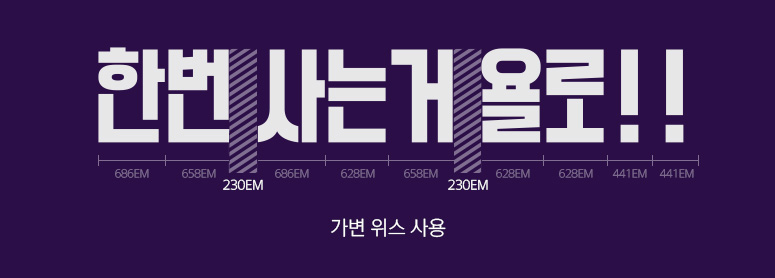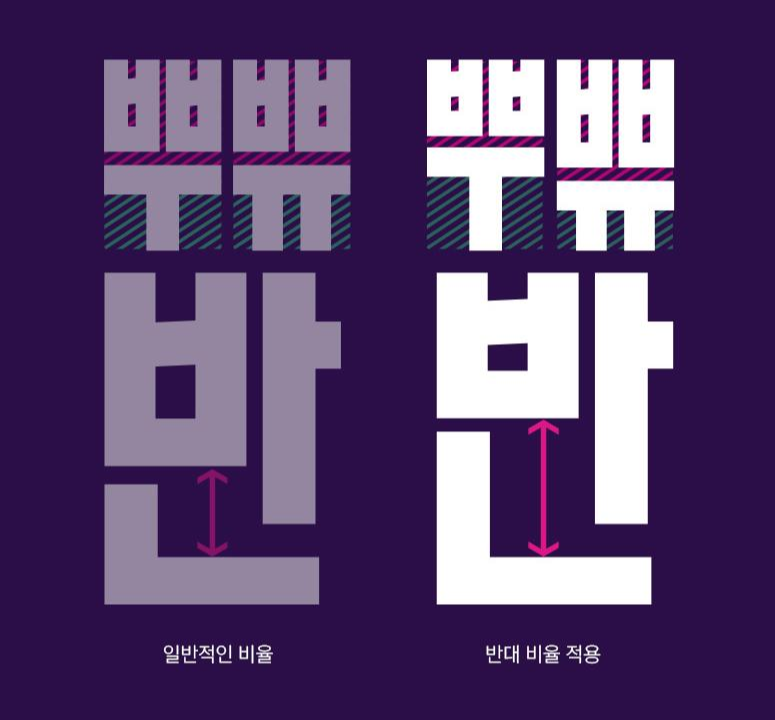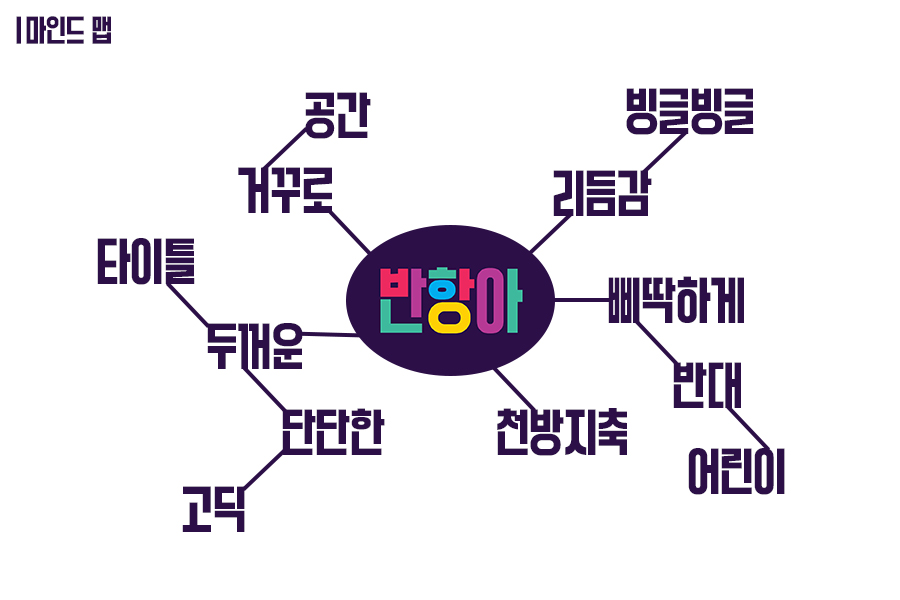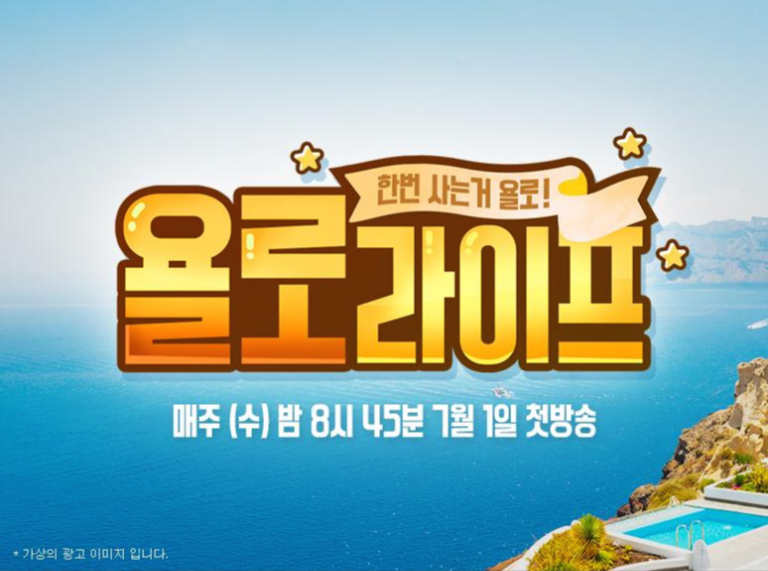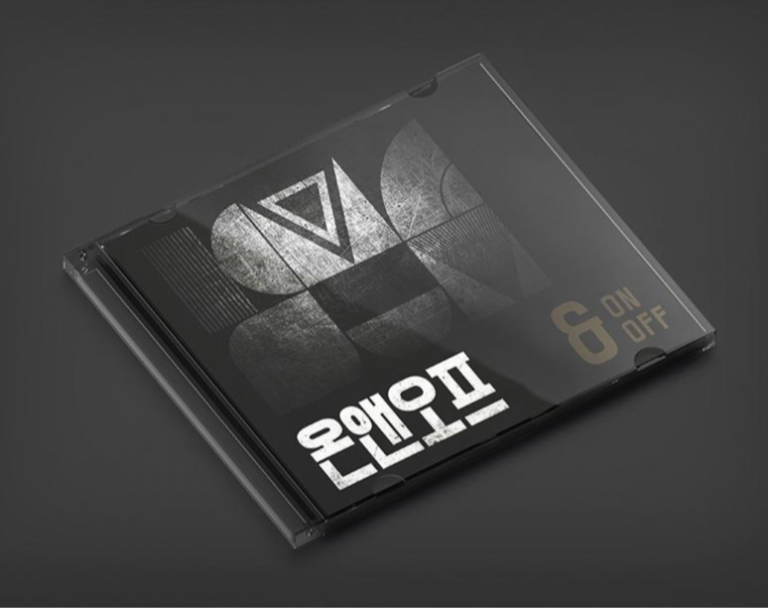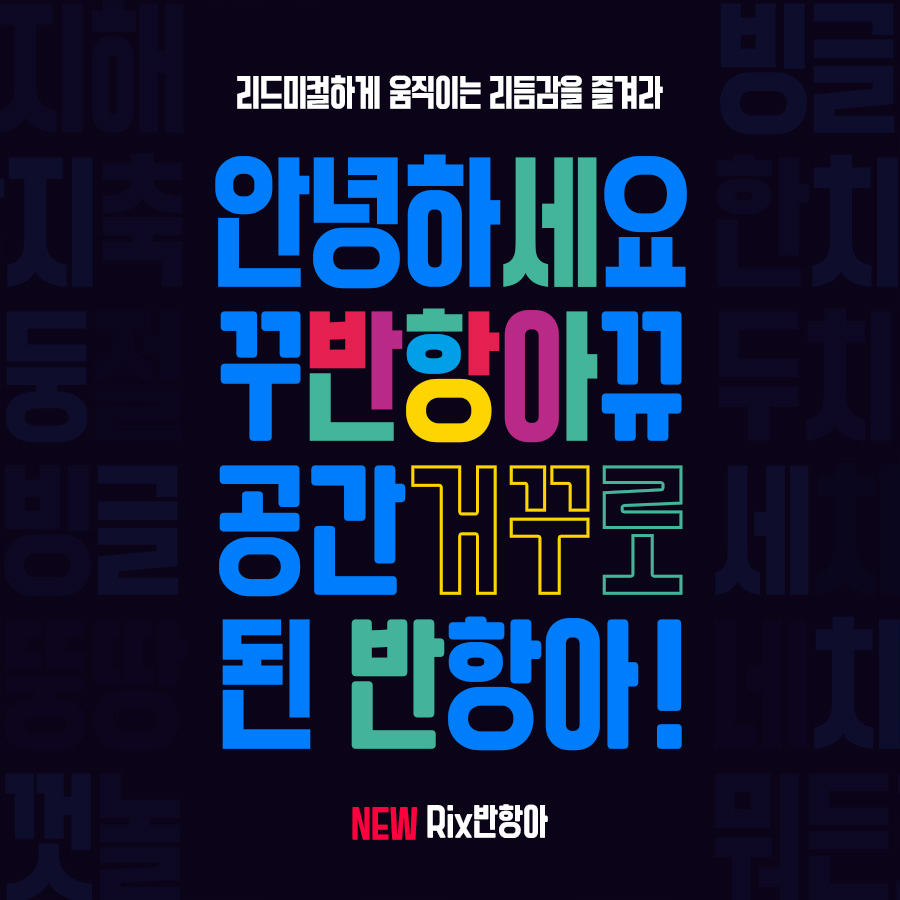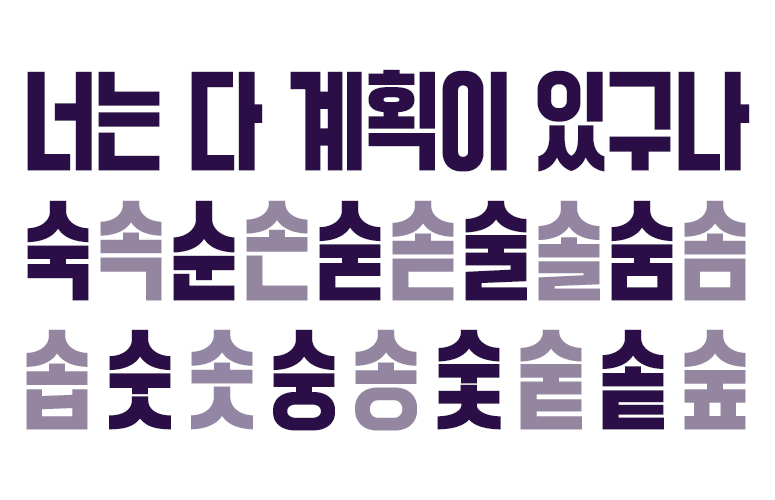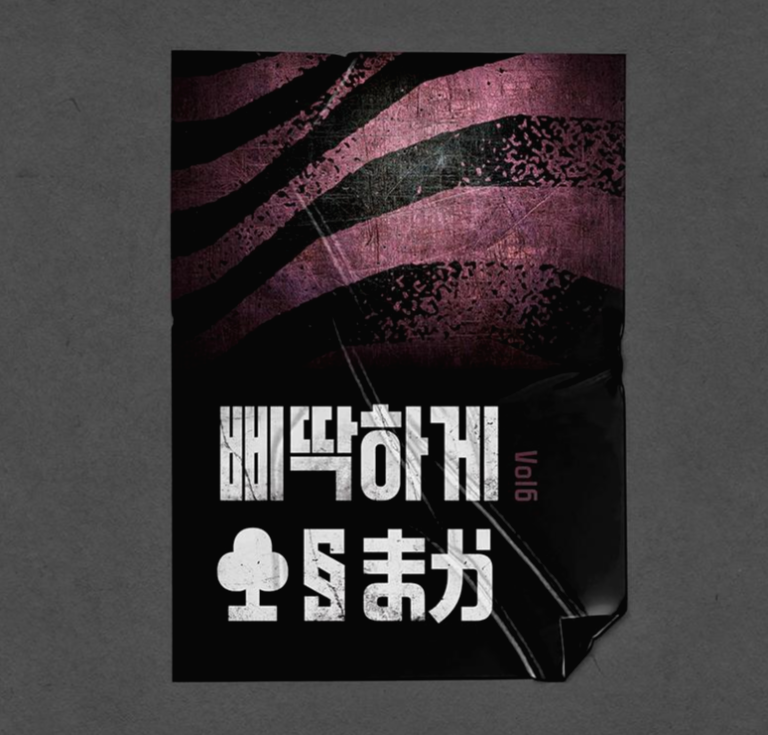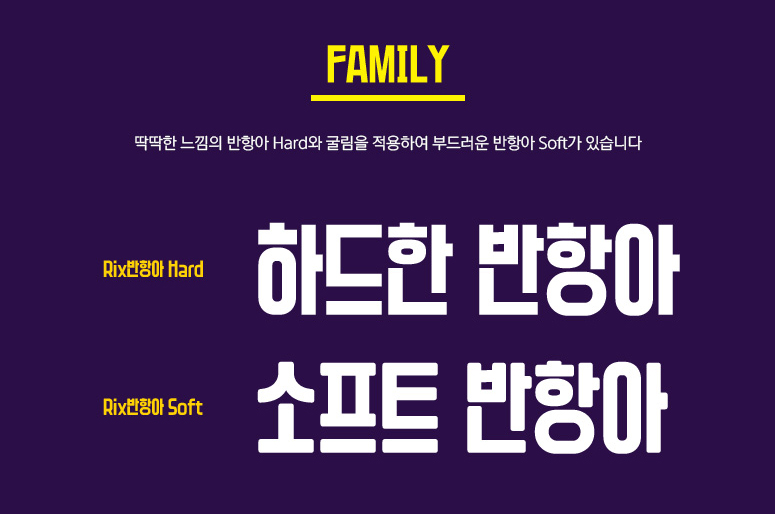
폰트의 고정관념을 바꾸다, Rix반항아
매달 가장 기다려지는 시간, 7월의 새로운 폰트가 나왔습니다. 바로 「Rix반항아」 서체인데요. 폰트에 대해 자세히 집중 탐구해보기 위해서 디자이너 인터뷰를 가지고 왔어요~ 폰트의 기획부터 디자인, 최종 출시까지 내 새끼(?) 같은 마음으로 공들였을 디자이너의 이야기! 재미있게 봐주세요.
폰트를 알려면 디자이너를 알아야지_폰트 디자이너 인터뷰
먼저 본인 소개 부탁해요!
안녕하세요. 전에 없던 폰트를 만들어내는 개척자가 되고 싶은 디자이너 박윤상입니다.
폰트에 뭔가 재밌는 요소를 더해 새로움을 주는 걸 좋아해요.
단도직입적으로다가. 이번에 출시된 ‘Rix반항아’ 서체의 특징을 딱 5글자로 표현하자면?
내 맘 대 로 해(!)
음, 와 닿네요(웃음) 제작하면서 재밌었던 에피소드나 웃픈 사연은 없었나요?
처음 기획했던 부분에서 동료들의 피드백을 받으면서 규칙들이 여러 번의 수정을 거쳐 제작이 되었는데요. 그러다 보니 제가 세워 놓은 규칙들이 헷갈려서 만드는 제작자인 저도 중간에 잘못 만들었던 부분이 있었다는 사실... 만들면서 엎치락뒤치락하느라 머리가 아팠습니다. (웃음)
'Rix반항아' 폰트를 제작하면서 가장 신경 쓴 부분은 어떤 것인가요?
아무래도 공간을 반대로 쓰다 보니 회색도가 안 맞으면 어쩌나 신경을 많이 썼던 것 같아요. 굵기를 같게 써버리면 획이 많은 부분하고 적은 부분 하고 이상해 보이더라고요. 그리고 한글과 어울리는 숫자, 영문, 일본어도 만드는데 아무래도 일본어는 완전 처음 디자인해봐서 신경을 많이 썼던 거 같아요.
폰트 디자인은 일반 사람들에겐 다소 생소할 수 있을 것 같아요. 어떻게 시작하게 되었나요?
대학교에 들어가면서 캘리그래피에 재미를 느껴서 처음에 붓펜과 납작펜으로 쓰는데 흥미를 느끼고 있었는데, 그 무렵 학교에서 타입페이스(Typeface:폰트) 수업이 새로 생겼어요. 제가 만든 글자가 컴퓨터에서 구현이 된다는 게 너무 신기하고 재미있었어요. 그래서 수업 맨 앞자리에서 듣다 보니 교수님 회사에서 인턴도 하게 되면서 마음을 굳히게 되었습니다.
폰트 한벌을 만들기가 굉장히 어렵지만 하나를 만들고 나면 너무 뿌듯하고 만족스럽습니다.
폰트 하나가 세상에 나오기 위해선 정말 긴 시간이 필요합니다. 새로운 폰트가 출시되기까지는 기획부터 최종 마무리까지 약 3~6개월의 기간(폰트의 스타일이나 몇 종의 패밀리가 나오느냐에 따라)이 소요된다고 해요! 생각보다 더 긴 시간인 것 같죠. 하나의 폰트가 나오기까지 디자이너의 노고가 얼마나 많을지. 그렇게 나오는 폰트인 만큼 적재적소에 알맞게, 더 많이 쓰이길 바라는 마음에서 이번 콘텐츠를 준비해 보았습니다.
폰트 이름은 이렇게 만들어집니다
디자이너가 작업한 폰트는 디자인이 나오면 마인드맵을 거쳐 새로운 이름을 얻게 됩니다. 서체 디자인을 보고 여러 직원들의 의견을 모아 만들어지는데요! 아래는 이미 완성된 이름이 가운데 들어가 있지만, 실제로는 가제를 놓고 떠오르는 생각들을 마구마구 적어줍니다. 폰트 디자인만 보고 떠오르는 이미지나 행동, 감정들을 자유롭게 적어 그 안에서 새로운 이름이 탄생하기도 합니다. 여러 사람들의 생각이 모여 조합되다 보니 생각지도 못한 아이디어나 단어들이 나올 때가 많아요. 정말 재미있는 과정 중 하나.
공간을 반대로, 고정관념 깨기
「Rix반항아」 서체의 가장 큰 특징은 바로 기존의 서체들과 달리 위아래 위위 아래(♪) 공간 배분을 반대로 한 것! 밑에 받침이나 자음의 높낮이가 계속 달라지는 것이 보이는데요~ 이 때문에 리듬감이 느껴지기도 합니다.
이렇게 보시면 확실히 다른 게 느껴지시죠? 밑에 받침 공간이 확 넓어진 글씨. 각각의 모음과 자음이 어떻게 조합되느냐에 따라 다른 공간이 적용되어 보는 재미가 있어요. 이런 독특한 특징이 다양한 이미지나 영상에 포인트를 줄 때 아주 유용하게 쓰일 것 같아요!
라틴확장에서도 한글에서 나타나는 독특한 공간을 동일하게 적용했어요. 색다른 스타일이 적용된 영문과 숫자 디자인. 글자를 써보면 어디 공간이 달라졌는지 찾아보는 것도 소소한 재미를 주는 듯합니다.
독특한 공간 배분 예시
「Rix반항아」 서체는 2가지의 패밀리(종류)로 구성되어 있습니다. 기본적으로 단단하게 딱 떨어지는 스타일의 Hard, 그리고 굴림을 적용해 좀 더 부드러운 느낌을 주는 Soft가 있어요. 같은 듯 다른 느낌으로 활용도 업. 정말 작은 디테일에도 신경을 많이 쓴 티가 나네요!
| Rix반항아 적용 이미지 샘플
TV에 나오는 광고 문구로도 손색이 없는 폰트예요. 텍스쳐 효과까지 넣으니 도톰한 「Rix반항아」 서체와 잘 어우러져 프로그램 타이틀로 찰떡같은 비주얼이네요.
이렇게 포스터나 앨범 커버 등 문구를 강조하고 싶은 어떤 시각물에도 활용할 수 있습니다. 독특한 공간적 특징이 눈길을 끌고, 단단한 고딕 서체가 베이스이기 때문에 가독성이 높습니다. 세로로 긴 형태감에서 오는 모던함과 굵기에서 오는 강한 임팩트, 그리고 일정하지 않은 글줄의 움직임으로 재미 요소를 더한 폰트입니다.